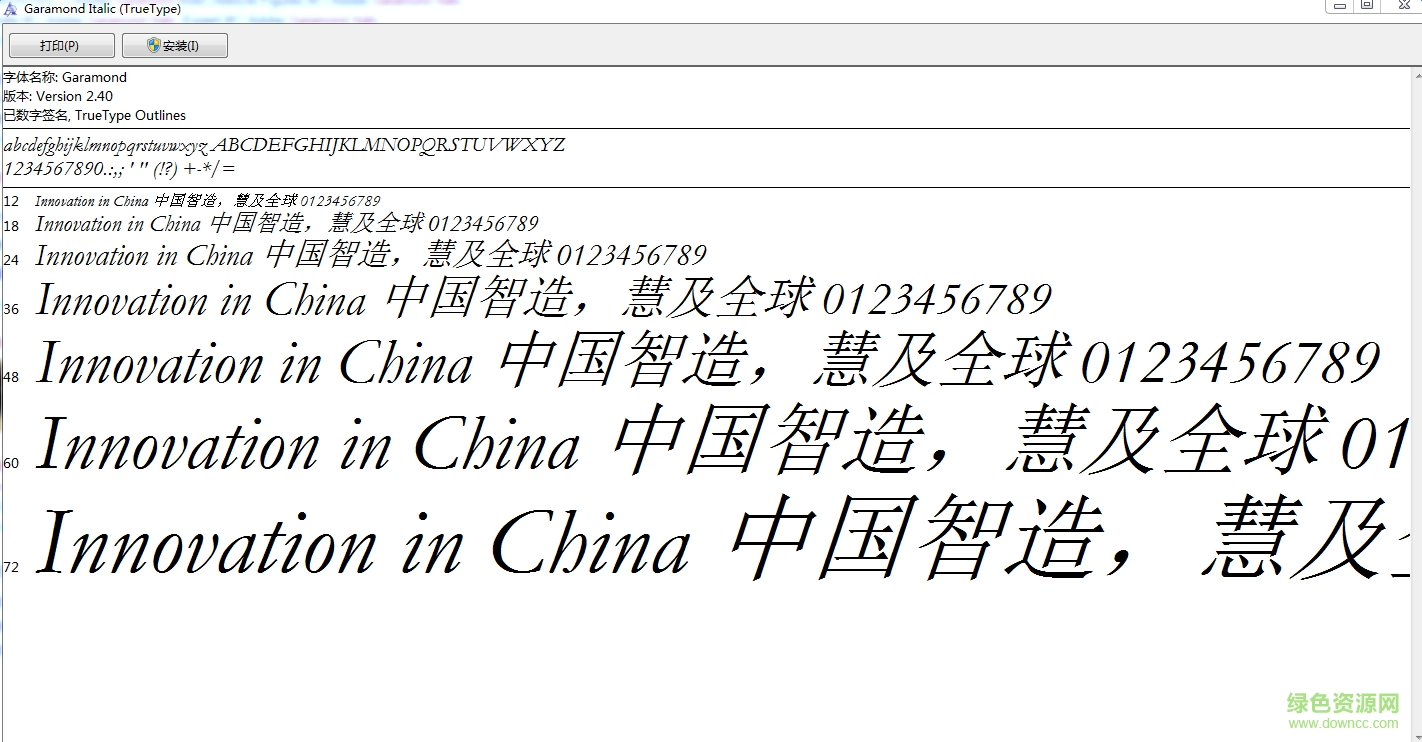
garamond italic變體是一款纖細(xì)傾斜的garamond字體,筆形犀利,空隙均勻,起落拐角舒展自如,可應(yīng)用于各類時(shí)尚書(shū)刊或廣告設(shè)計(jì)中!有需要者歡迎在綠色資源網(wǎng)下載!
Garamond是個(gè)用途廣泛的字體,蘋(píng)果用它,國(guó)外的高級(jí)餐廳Menu用它。Garamond的易讀性非常高,由于它適合大量且長(zhǎng)時(shí)間的閱讀,幾百年來(lái)西方文學(xué)著作常用Garamond來(lái)作內(nèi)文的編輯。